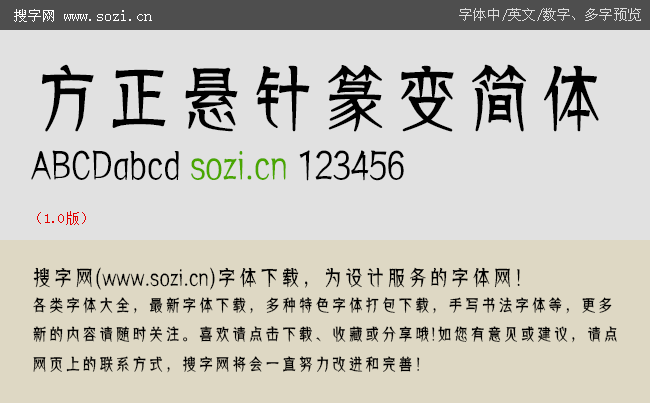
方正懸針篆變簡(jiǎn)體
搜字網(wǎng)給大家提供一款帶上古典風(fēng)味的方正懸針篆變簡(jiǎn)體下載。方正懸針篆變字體意在保留篆書韻味,同時(shí)將隸書與楷書筆畫特征熔于一爐,實(shí)為三種書體的統(tǒng)一。將傳統(tǒng)書法藝術(shù)與現(xiàn)代形式語匯融合,追求裝飾性及藝術(shù)美感,端莊秀美、開張疏朗,雍容大氣、復(fù)古卻易讀。主要適用于需要古典裝飾風(fēng)格的大、小標(biāo)題及廣告、電子游戲、古籍讀物等用字。